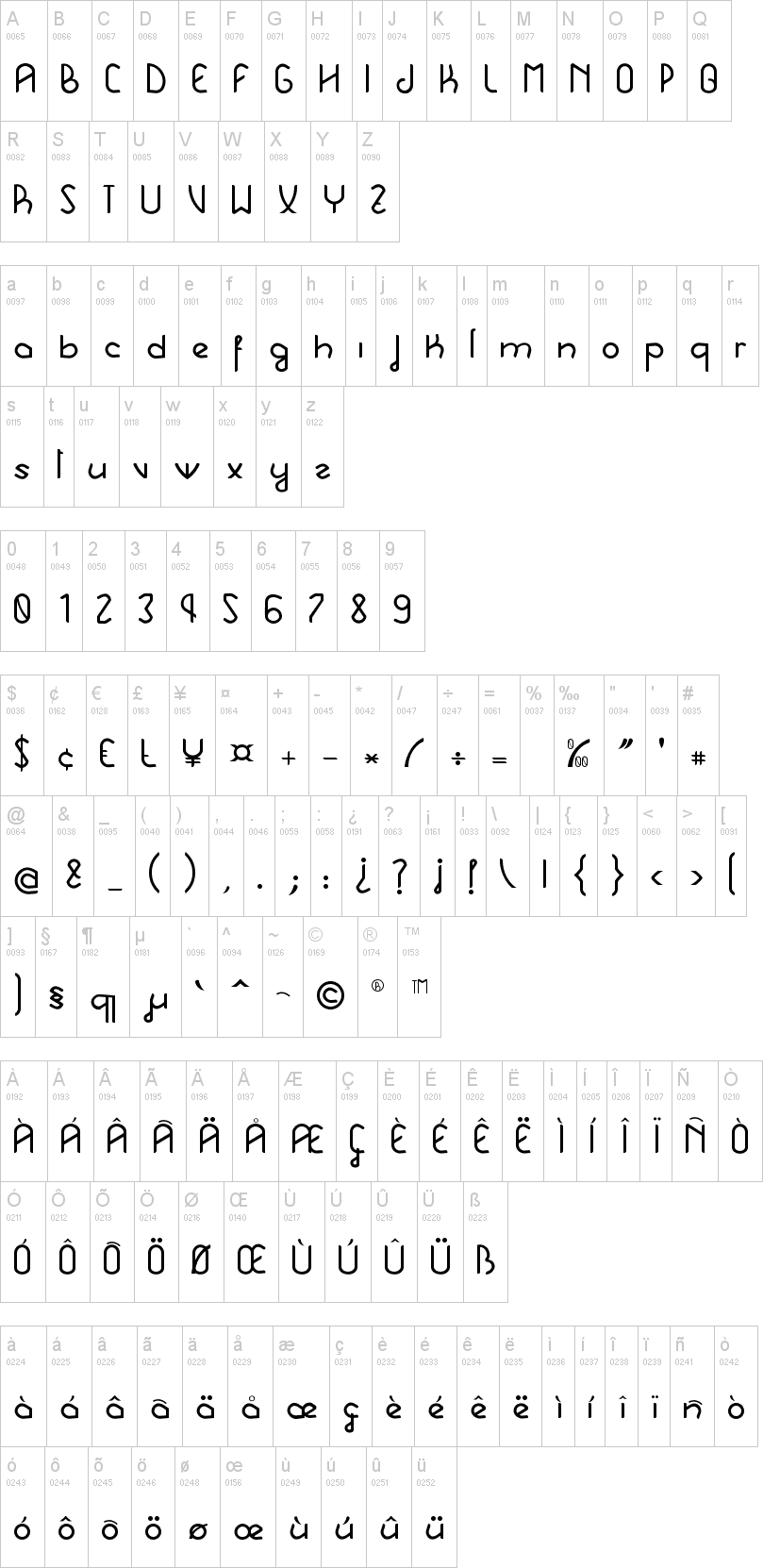
Hebe 字体是一款简洁大方的英文字体,由设计师 Alex Kaczun 设计。Hebe 字体的字母笔画细腻、流畅,给人以温柔、活泼的感觉,极具可读性,特别适合用于报刊、封面、标识、标题等场景。Hebe 字体拥有 5 种字重,包括 Regular、SemiBold、Bold、Heavy 和 Black,可以满足不同的设计需求。内容介绍
Hebe是一款非常不错的手写艺术字体,具有很好的视觉感,适合于文化类的宣传设计、商业类品牌的广告和产品包装设计以及个性化文字排版等较多场景。